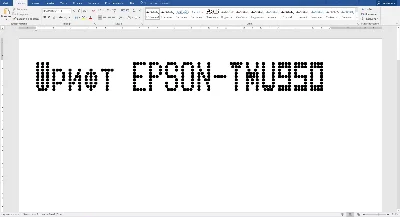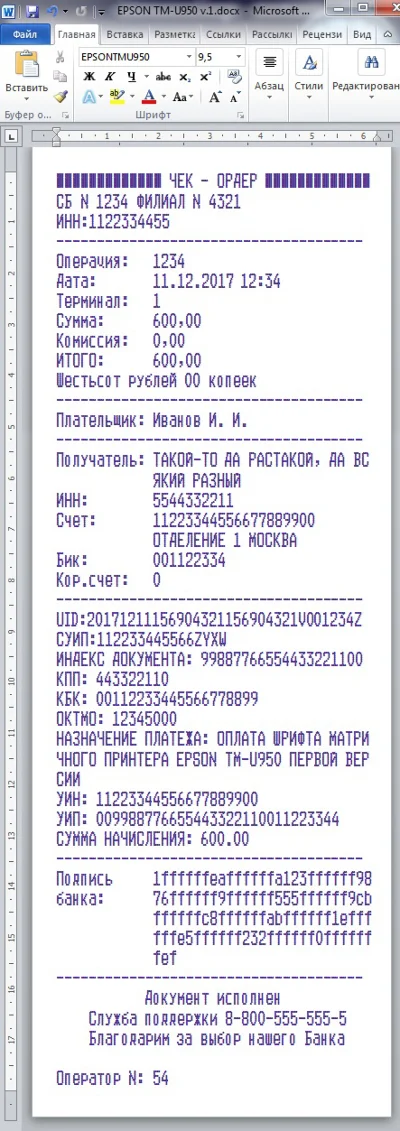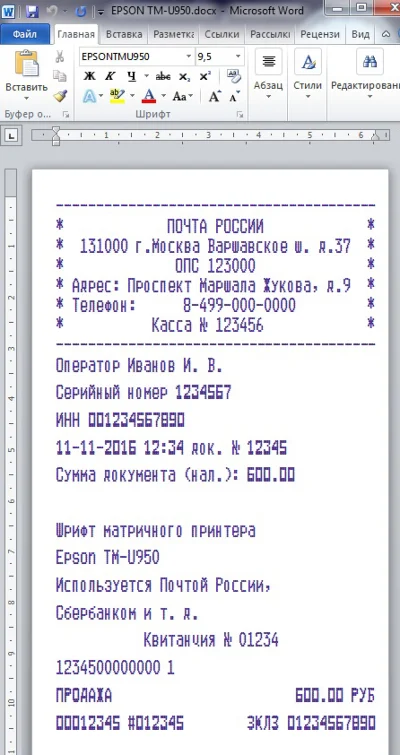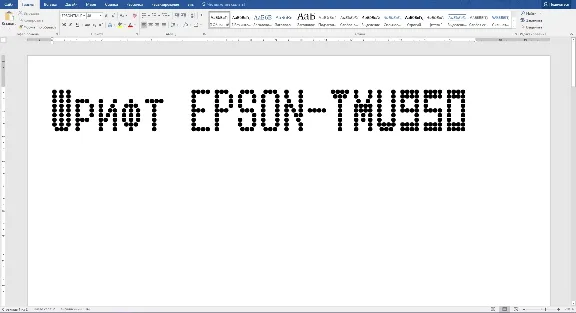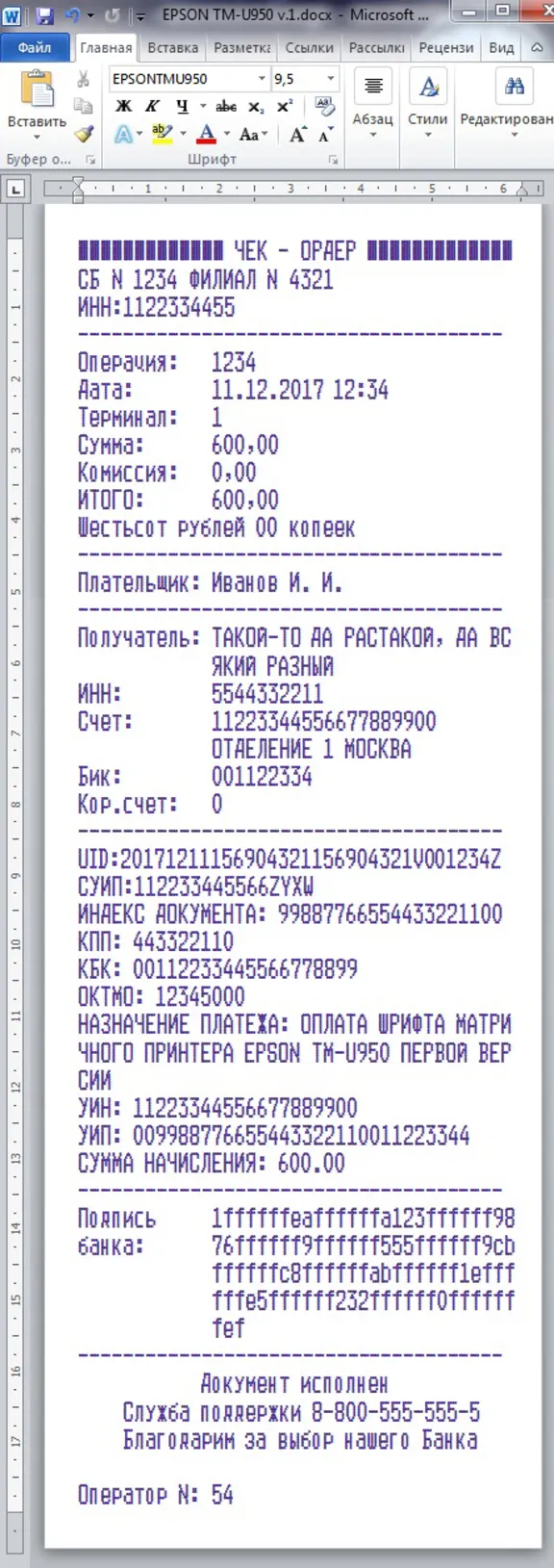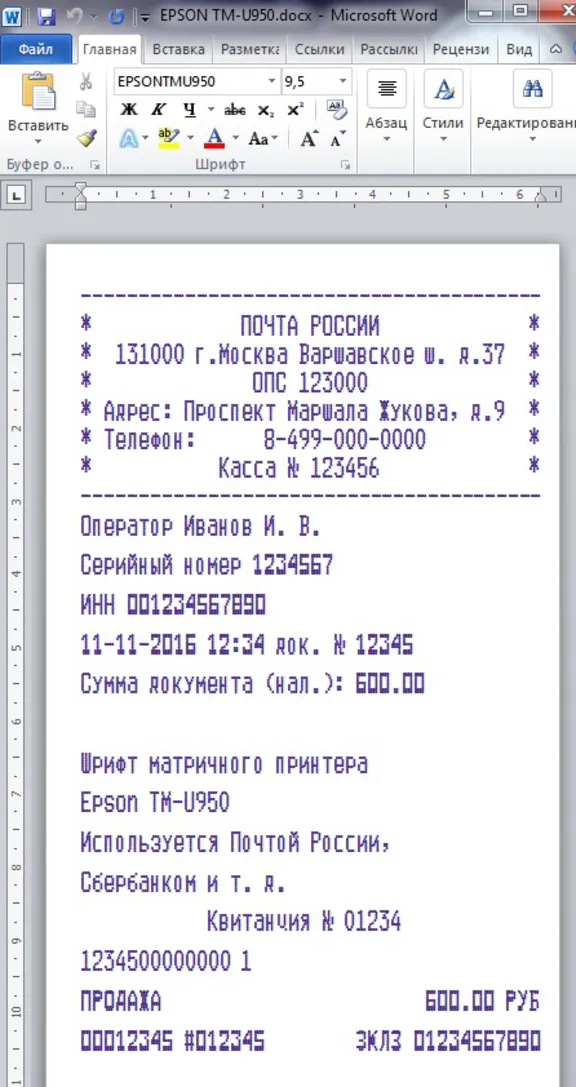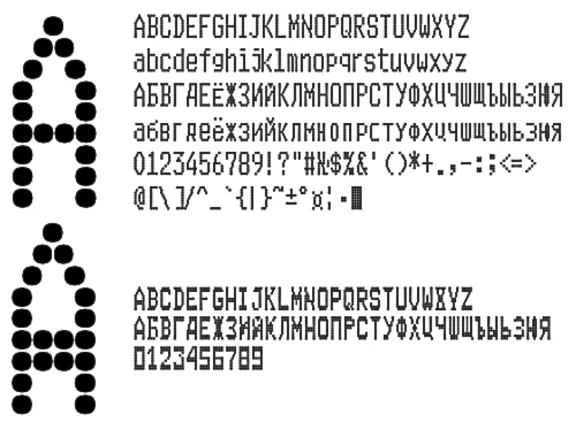
Шрифт матричного принтера Epson TM-U950 первой версии,который используется для печати чеков, квитанций, билетов многими банками,в частности, Сбербанком, отделениями Почты России и другими крупными организациями. Шрифт(матрица 7×9) в формате TTF(русские и английские буквы)для использования в программе Microsoft Word. В архиве находятся обычный и жирный шрифты в формате TTF и шаблон чека. Вам остается только установить шрифт в систему (обычно C:\WINDOWS\Fonts), открыть шаблон и начать редактирование.
Благодаря сотрудничеству с одним из покупателей, шрифт был оптимизирован под размер печатающей головки стандартного матричного принтера EPSON, для печати "точка в точку". Однако шрифтом можно пользоваться как и любым другим - печатать на любом принтере.